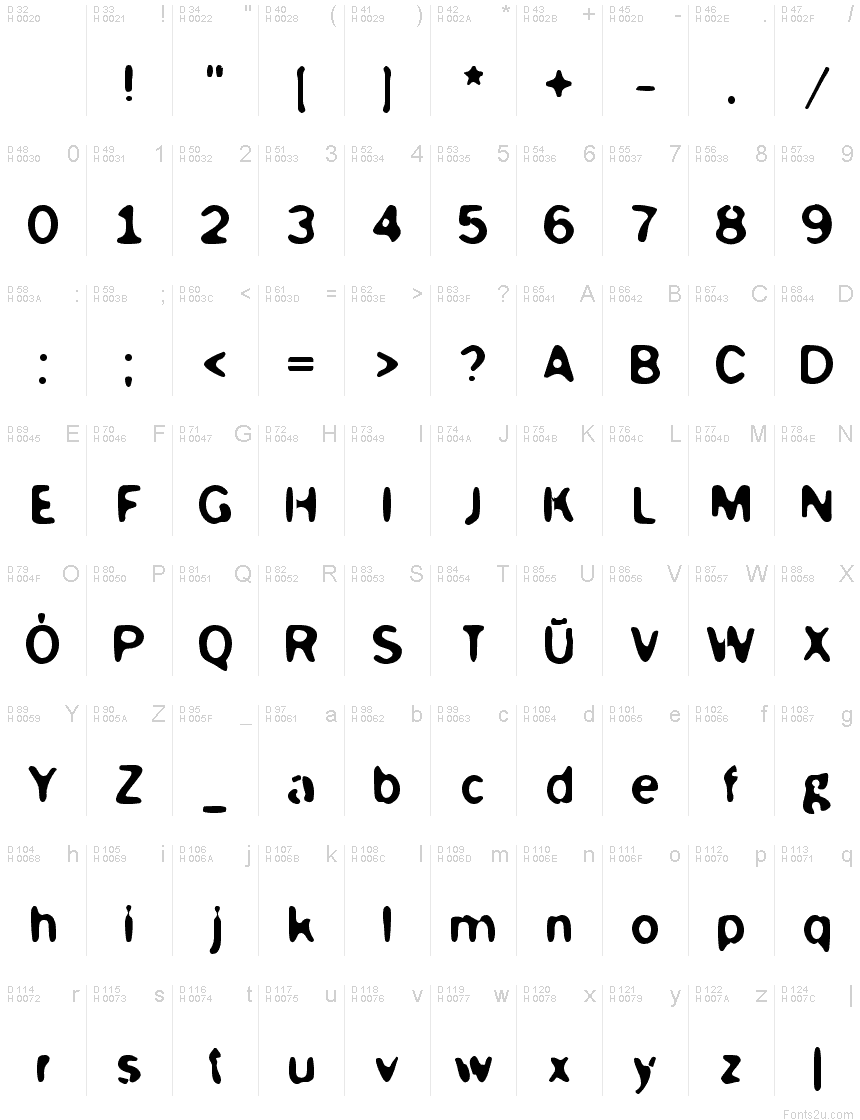
McKoy هو خط عرض (display) مجاني وعضوي يتميز بلمسة حرة وكأنه منحوت يدوياً. تبدو الحروف ناعمة وممتلئة، ثم تنقبض فجأة أو تنكسر لتشكل نتوءات وخدوشاً صغيرة، مما يضفي على الخط إيقاعاً مرحاً ومتهالكاً بعض الشيء، يميل إلى النمط القديم (الريترو) دون التقيد بعقد زمني معين.
إنه مناسب لنشرات الموسيقى، وتغليف منتجات الأطفال، وأغلفة المجلات المستقلة، ولافتات المتاجر، وأعمال الشعار القصيرة حيث يمكن للأشكال أن تعبر عن نفسها. وباعتباره خطاً مجانياً، يعمل McKoy بشكل جيد أيضاً مع العناوين والاقتباسات الكبيرة، خاصة عندما تبحث عن حروف عريضة تبدو عفوية وغريبة ومصنوعة يدوياً بشكل لا لبس فيه.